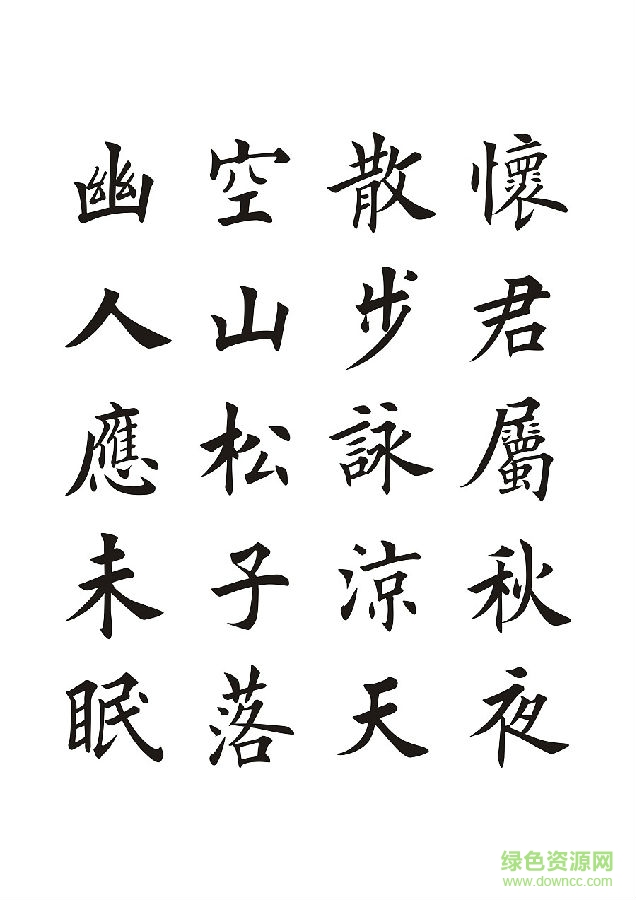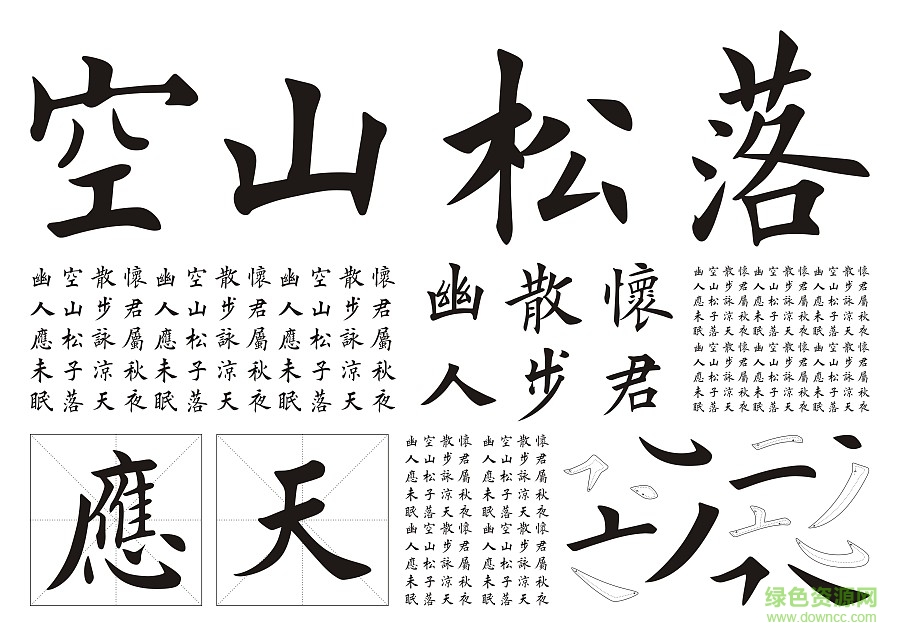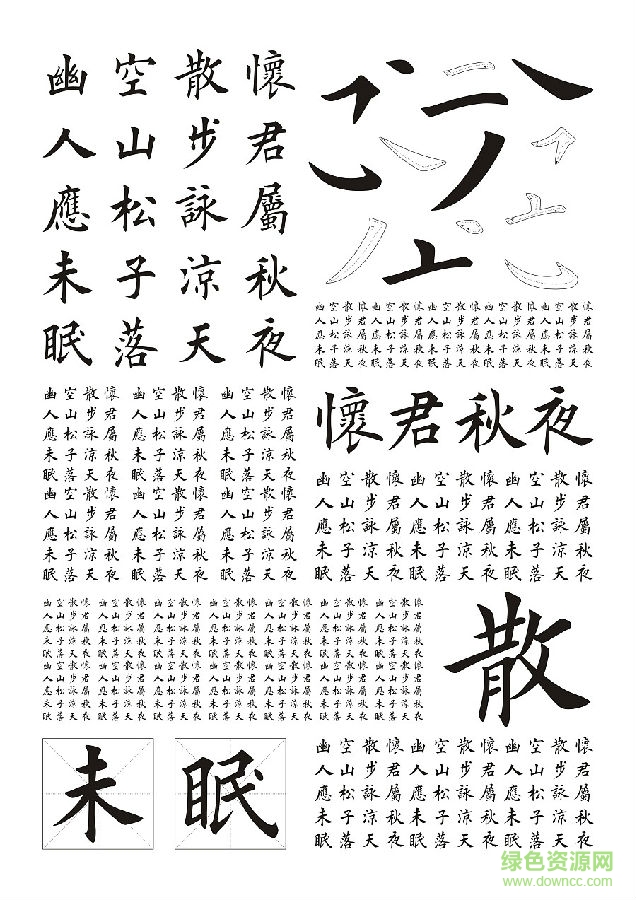
“彥辰歐楷”是中國大陸境內(nèi)第一款歐體(歐陽詢)計算機書法字體(字庫)產(chǎn)品,作品糅合歐陽詢《九成宮醴泉銘》及當(dāng)代書法寫歐諸家,將歐體字重新做了結(jié)構(gòu)解析,使字形更加疏朗空靈,營造更多的空間感,在識別上更加輕盈清新。
字體設(shè)計常常需要取材傳統(tǒng)書法,難點就在如何集萃歷史上代表性書法家的書作精華,根據(jù)印刷技術(shù)和平面設(shè)計的需求與運用特點,將其與現(xiàn)代造字技術(shù)結(jié)合?!皬┏綒W楷”的設(shè)計師將各代的習(xí)歐、寫歐書法家作品融合,去除書寫習(xí)氣,賦予其現(xiàn)代平整與規(guī)律性的美感,形成具有時代新意的書法字形,使其在保持疏朗空靈的傳統(tǒng)風(fēng)格的同時,具備識別性和印刷的規(guī)范性。